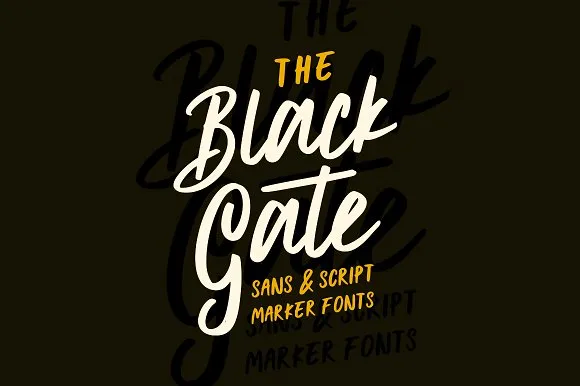
Black Gate Typeface
Aqui está uma descrição em português para a página de download da fonte ‘Black Gate Typeface’, seguindo as instruções fornecidas: Introduzimos Black Gate Typeface! Desenhada por Angga Mahardika, esta é uma fonte premium vendida na Creativemarket. Agora, é gratuita para baixar. Inspirada em letras de sinalização e propaganda vintage, a fonte ‘Black Gate’ tem como objetivo mesclar o estilo das fonts sans serif com script, resultando num toque natural dos anos 50. Esta fonte é perfeita para uma variedade de aplicativos gráficos – desde identidades corporativas e cartões de visita até adesivos e material publicitário. Suas linhas retas e seus traços distintos oferecem um touch moderno à vez que se mantêm fiéis a um design vintage. Com Black Gate, seu projeto ganhará uma personalidade única, destacando-se na sua categoria. A fonte não apenas reúne as melhores características do tipo sans serif, mas também incorpora elementos de estilo script, criando um mix inovador e único que se destaca da concorrência. Sua simplicidade e facilidade de uso fazem dela uma escolha ótima para designers em busca de um estilo clássico moderno. Seja você um designer gráfico ou alguém que deseja adicionar um toque especial a seus trabalhos, Black Gate é uma opção perfeita para seu projeto. Não hesite em experimentar e ver como essa fonte pode revolucionar suas criações!